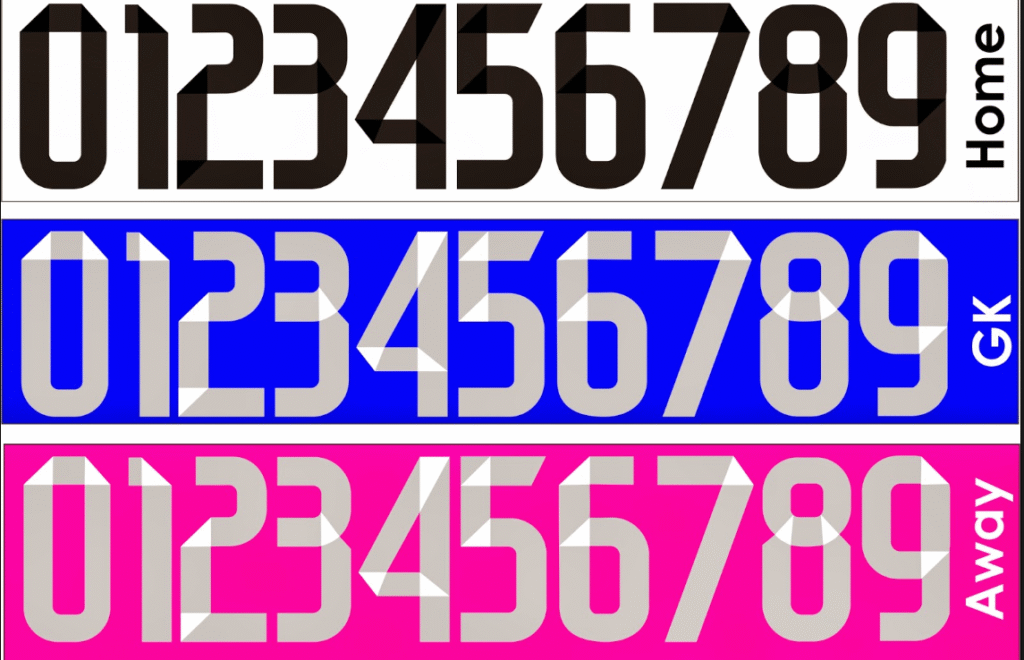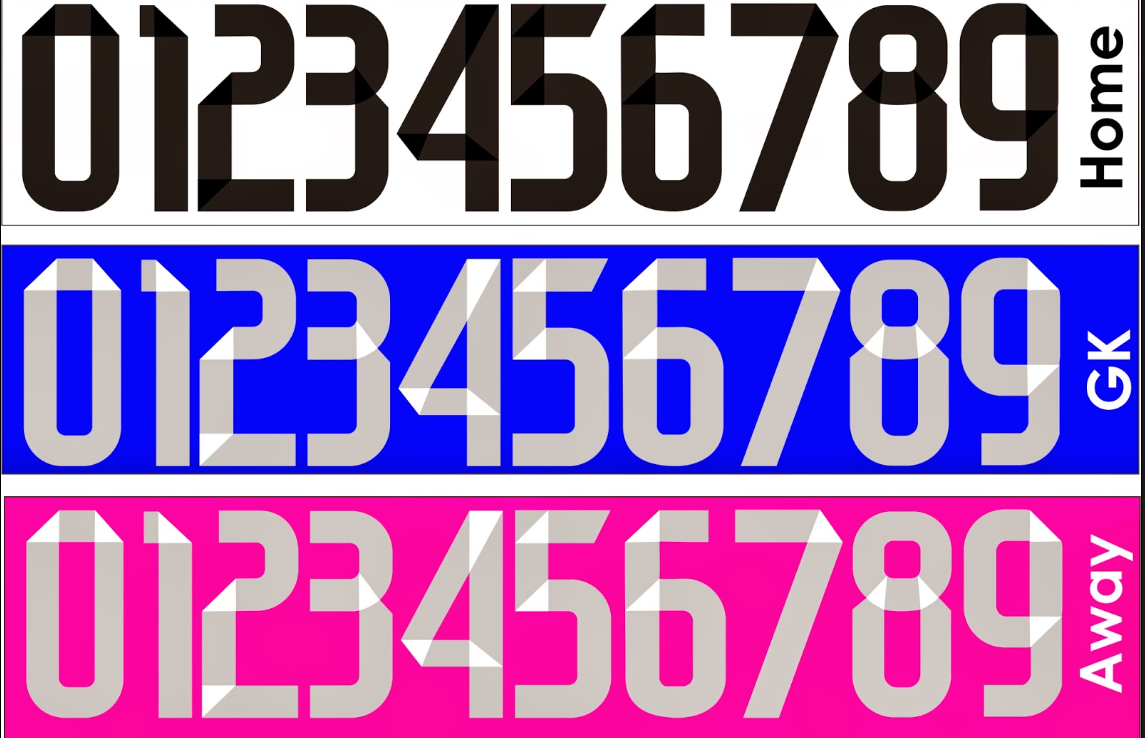
Reviva uma das épocas mais estelares do futebol mundial. A temporada 2014-2015 do Real Madrid não foi apenas marcada por grandes jogadas de Cristiano Ronaldo, Bale e Benzema, mas também por uniformes icônicos desenhados pela Adidas.
Se você deseja recriar a personalização histórica do manto Merengue — seja a clássica camisa branca com detalhes pretos ou o polêmico e inesquecível uniforme rosa (Away) —, este arquivo é a peça que faltava no seu projeto. Trata-se da tipografia exata usada em La Liga e na Champions League naquela temporada.
Estilo Visual e Aplicação
A fonte desenvolvida pela Adidas para o Real Madrid nesta temporada aposta em um minimalismo funcional. É uma tipografia sans-serif (sem serifa) com espessura média, o que garante excelente legibilidade à distância.
Os números possuem cortes internos discretos e traços ligeiramente arredondados nas bordas, fugindo do estilo quadrado rígido de anos anteriores. Essa fonte transmite modernidade e limpeza, harmonizando perfeitamente com a elegância da camisa titular e equilibrando o visual ousado da camisa rosa “fúcsia”. É ideal para personalização de camisas retrô, banners digitais ou restauração de peças de colecionador.